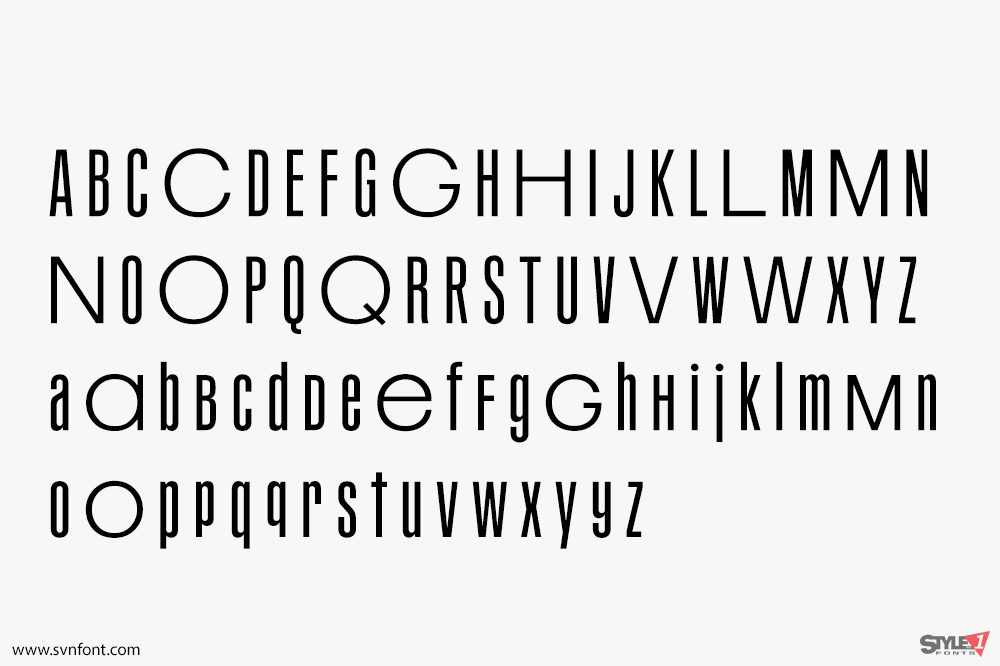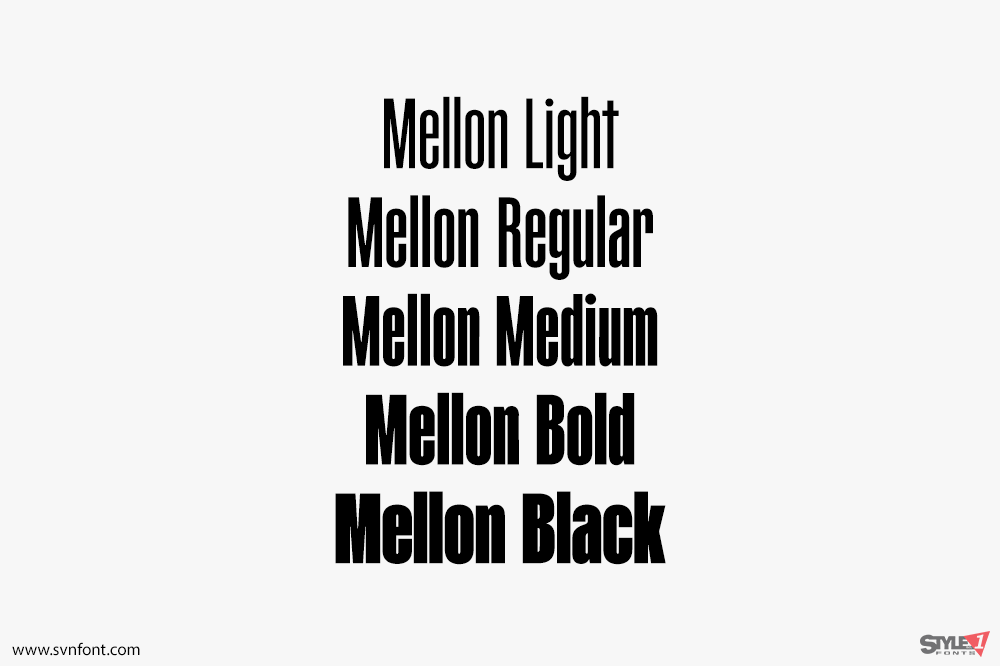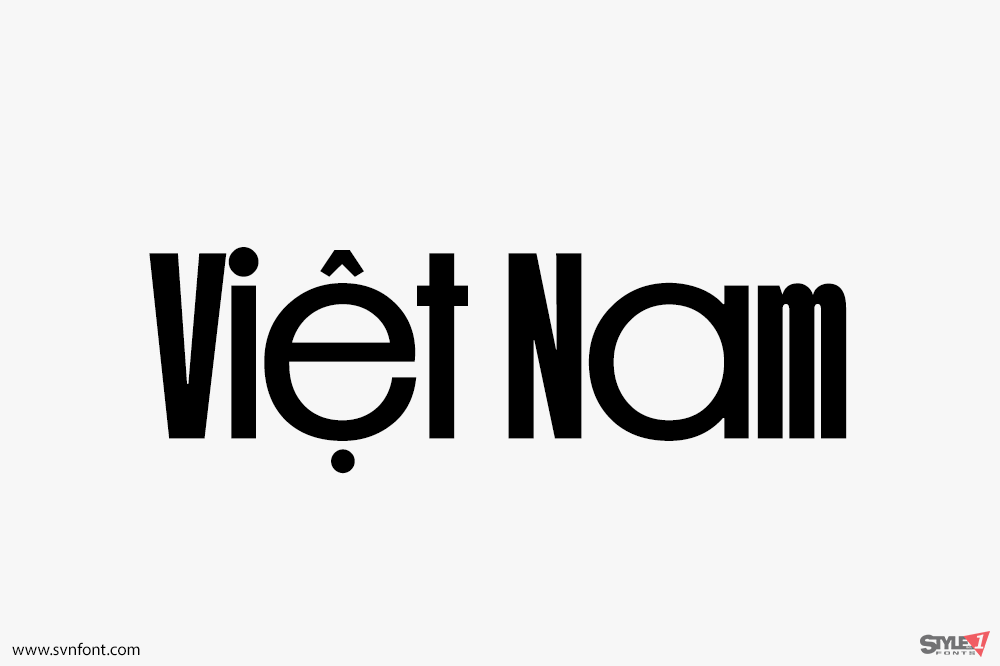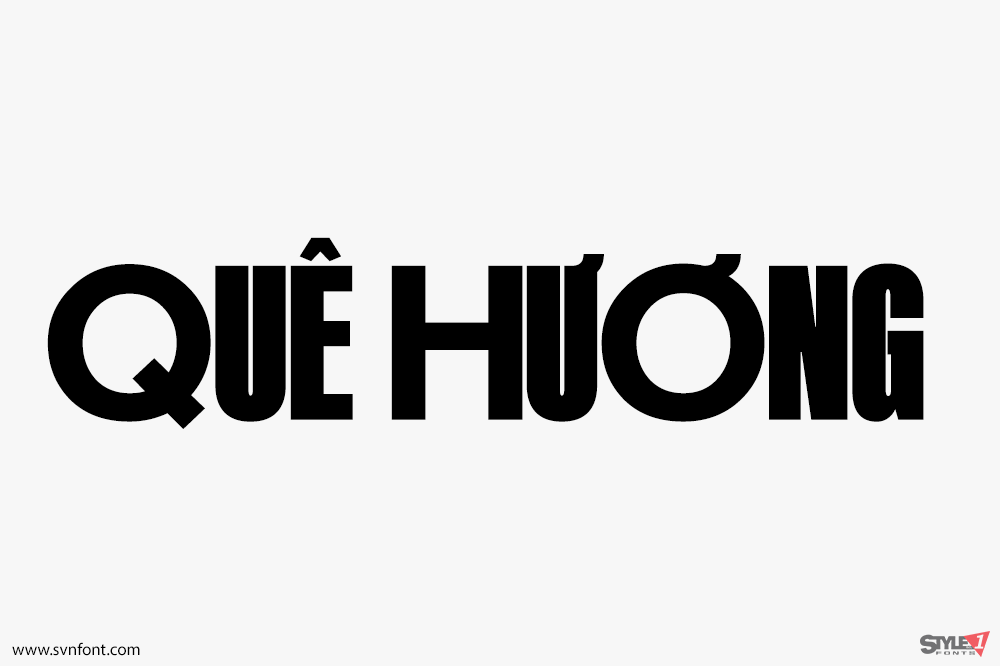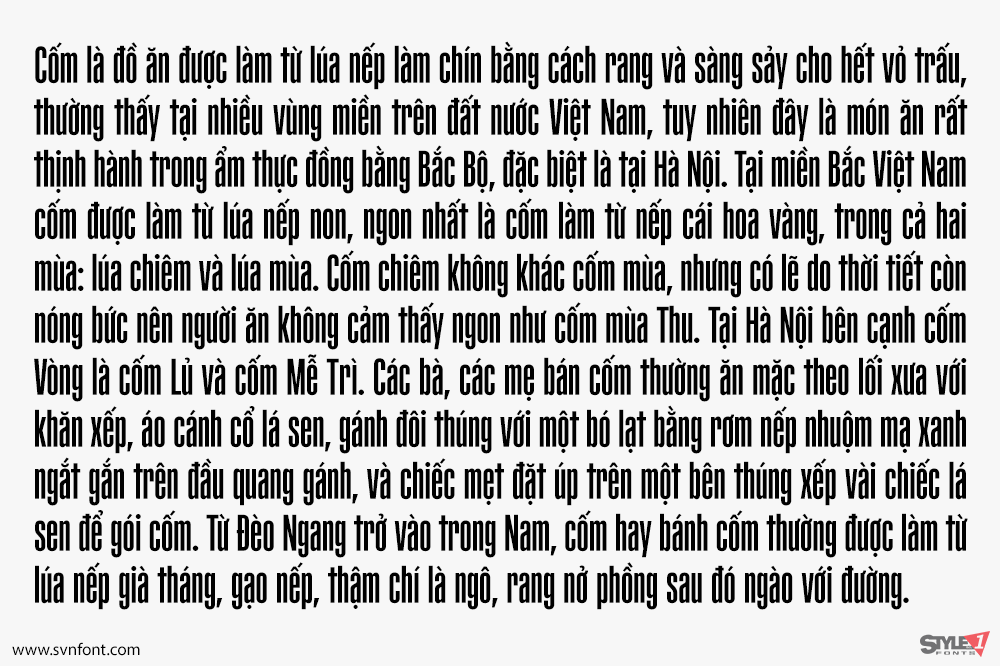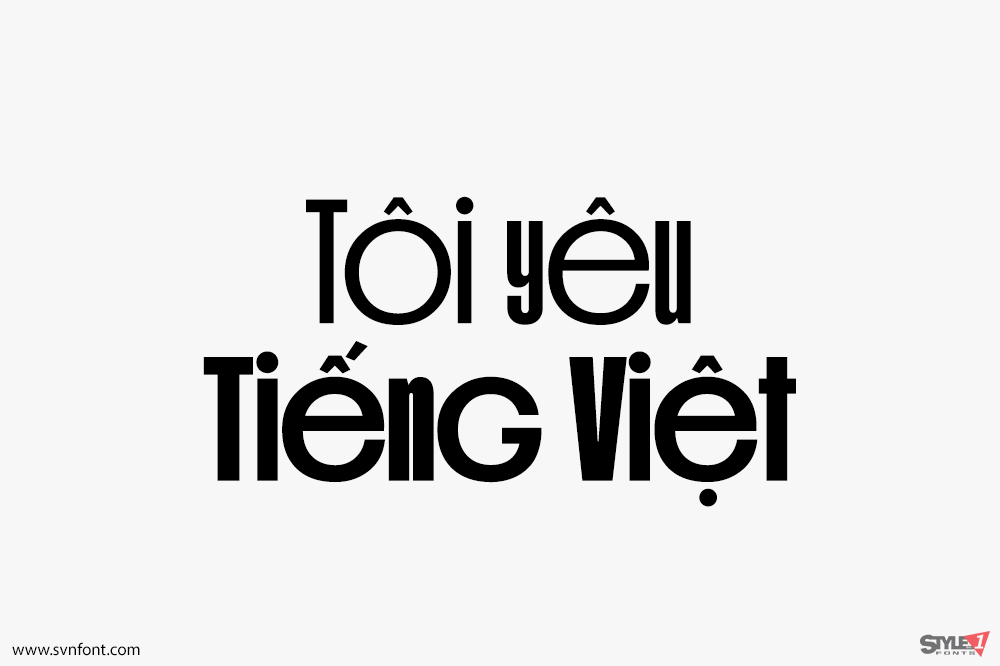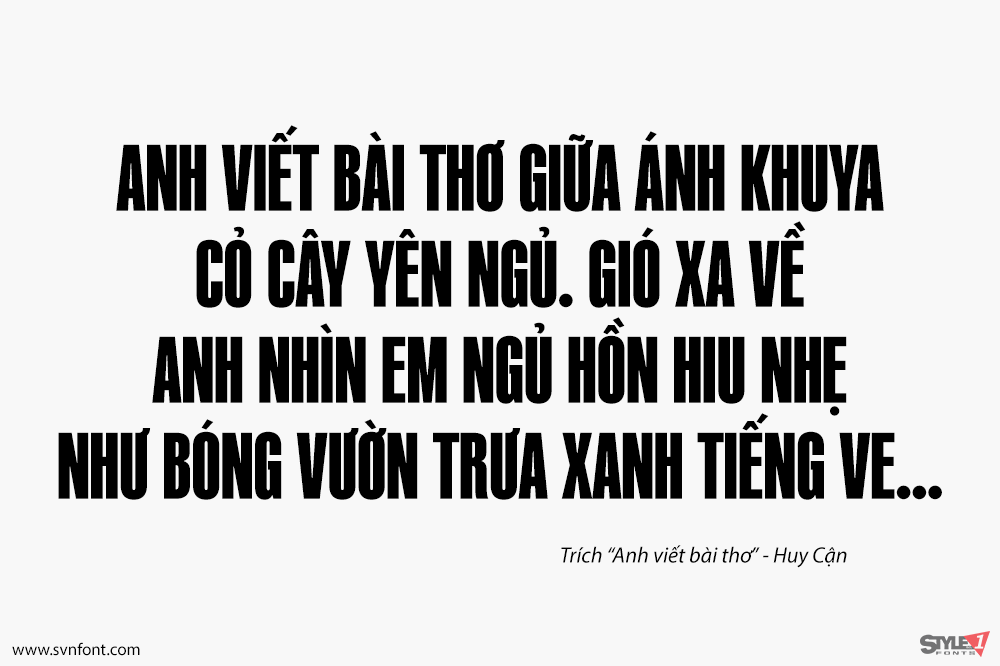
PF Mellon là một phông chữ grotesque biến đổi theo phong cách hiện đại với nguồn gốc đa dạng. Tính thẩm mỹ độc đáo của nó là kết quả của việc khám phá nghệ thuật nhấn mạnh các tiêu đề, dòng chính và văn bản theo những cách hấp dẫn và bất ngờ.
Trái ngược với thông lệ thông thường là làm nổi bật văn bản bằng các độ đậm nặng hơn, PF Mellon đề xuất một cách thức mới đầy hấp dẫn dựa trên các bố cục gây chú ý và thu hút của các hình dạng chữ hẹp và mở rộng — ngay cả khi được đặt ở dạng chữ thường. Mang một phần của phong cách hình học và một phần của phong cách grotesque, bảng chữ cái biểu hiện và phong cách xa hoa của PF Mellon thách thức các quy ước của văn hóa thị giác theo cách gợi nhớ đến phong trào Art Deco.
Tính đặc thù nổi loạn của PF Mellon được lấy cảm hứng từ cá tính độc đáo của phông chữ PF Venue nổi tiếng của chúng tôi, một phông sans serif hình học trước đó được đặc trưng bởi sự kết hợp táo bạo của các cấu trúc không đồng nhất. Bộ khung thiết kế cơ bản của PF Mellon chịu ảnh hưởng từ các phông chữ sans serif nén từ thế kỷ 19 và đầu thế kỷ 20, như Grotesque No.77 của Stephenson Blake và Alternate Gothic của ATF, đồng thời thêm độ tương phản vào độ dày của các nét. PF Mellon cũng có sẵn ở định dạng phông chữ biến đổi (variable font) mà bạn có thể yêu cầu miễn phí từ Parachute® sau khi mua toàn bộ bộ phông chữ.
Nhà thiết kế: Panos Vassiliou
Nhà phát hành: Parachute